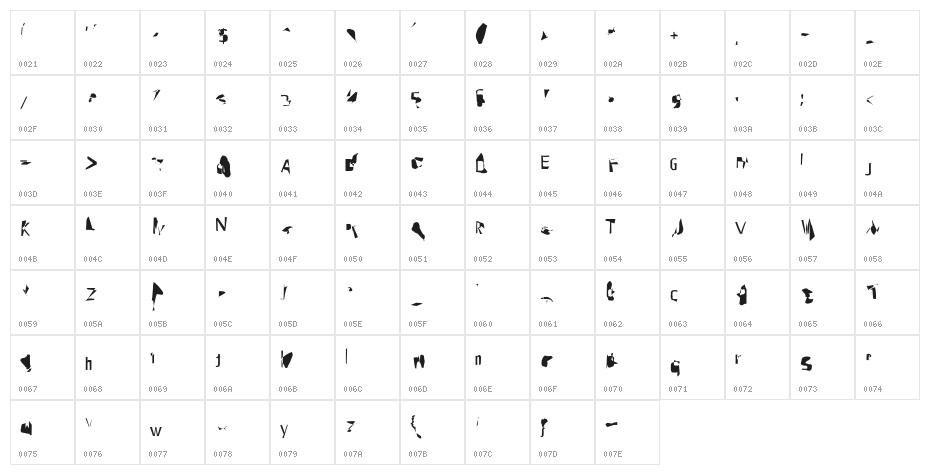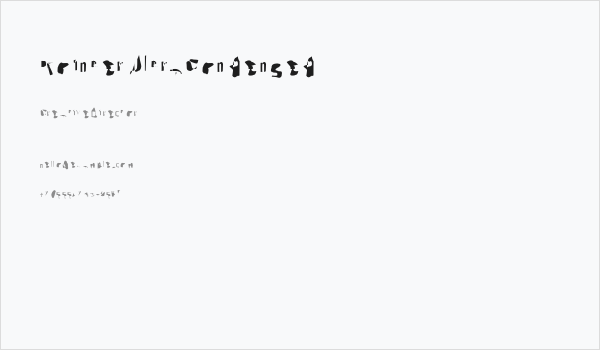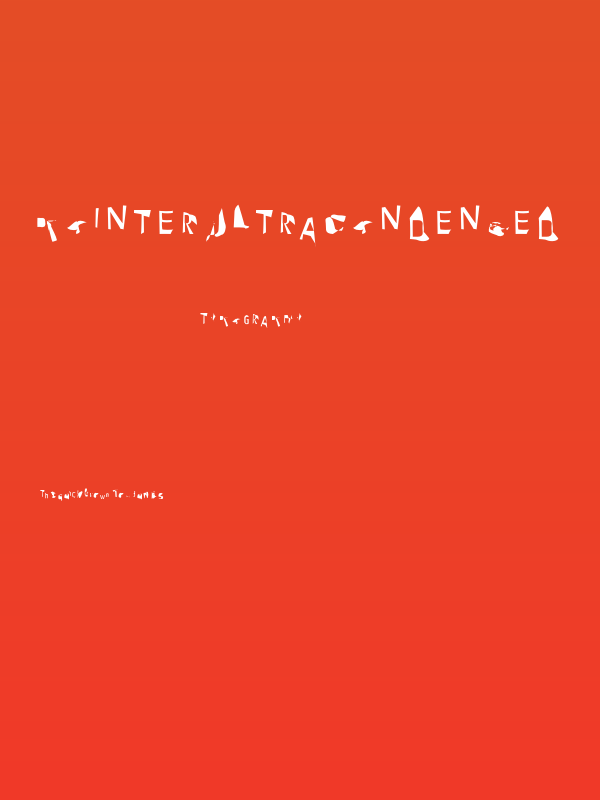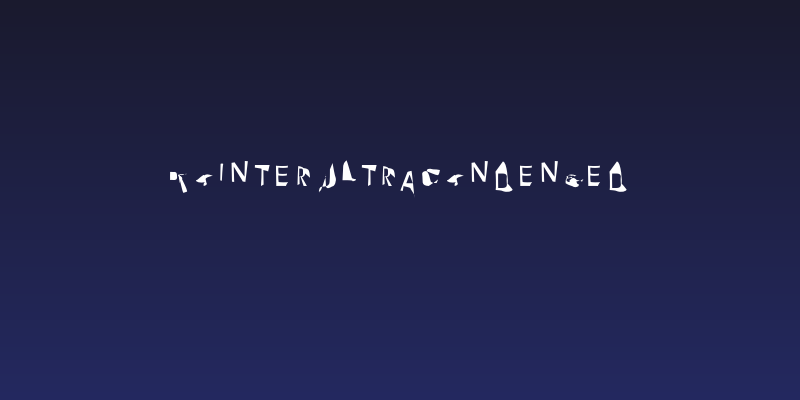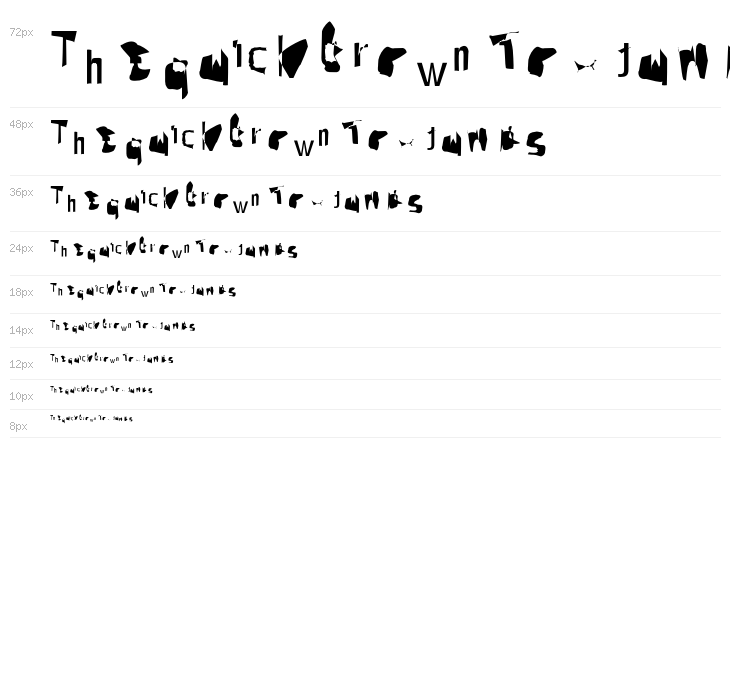
Pointer UltraCondensed Font
✎ Distorted Eroded
| الفئات | Distorted Eroded |
| العرض | Condensed |
| النمط العام | Modern, Avant-garde |
| حالة الاستخدام | Headlines, Artistic projects, Branding |
| مشاريع مقترحة | Ideal for album covers, modern art posters, experimental design projects, and edgy branding. |